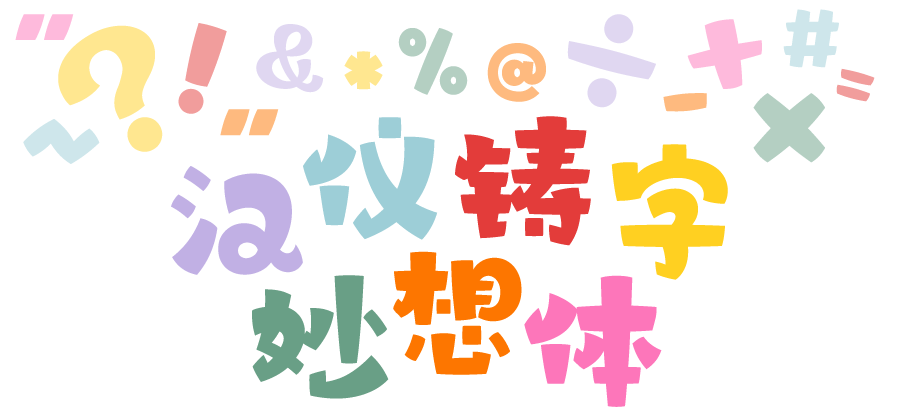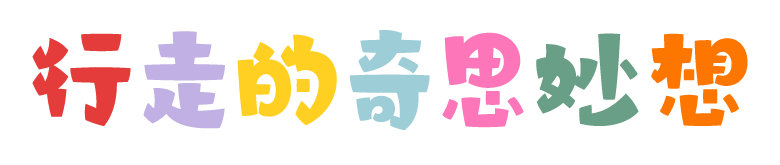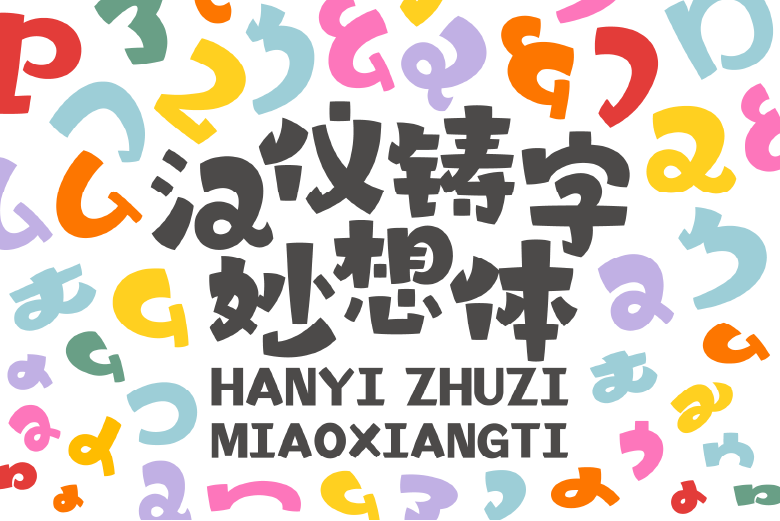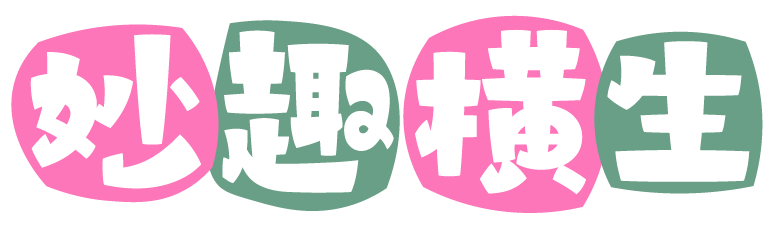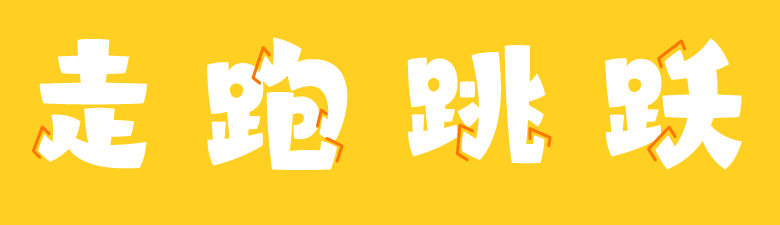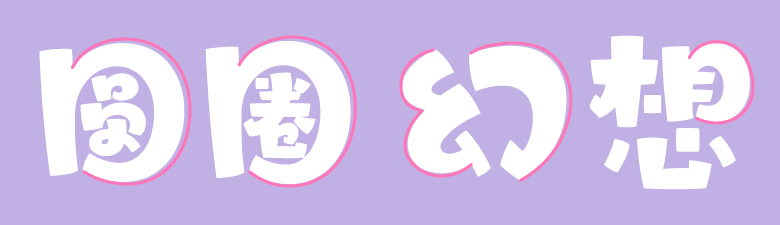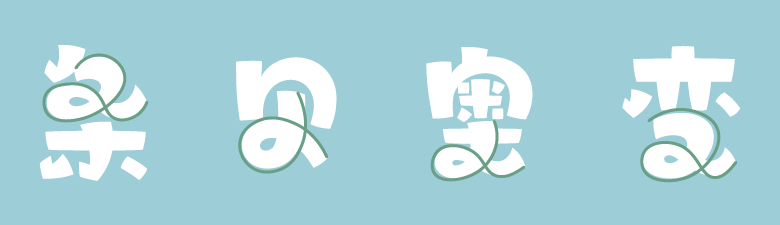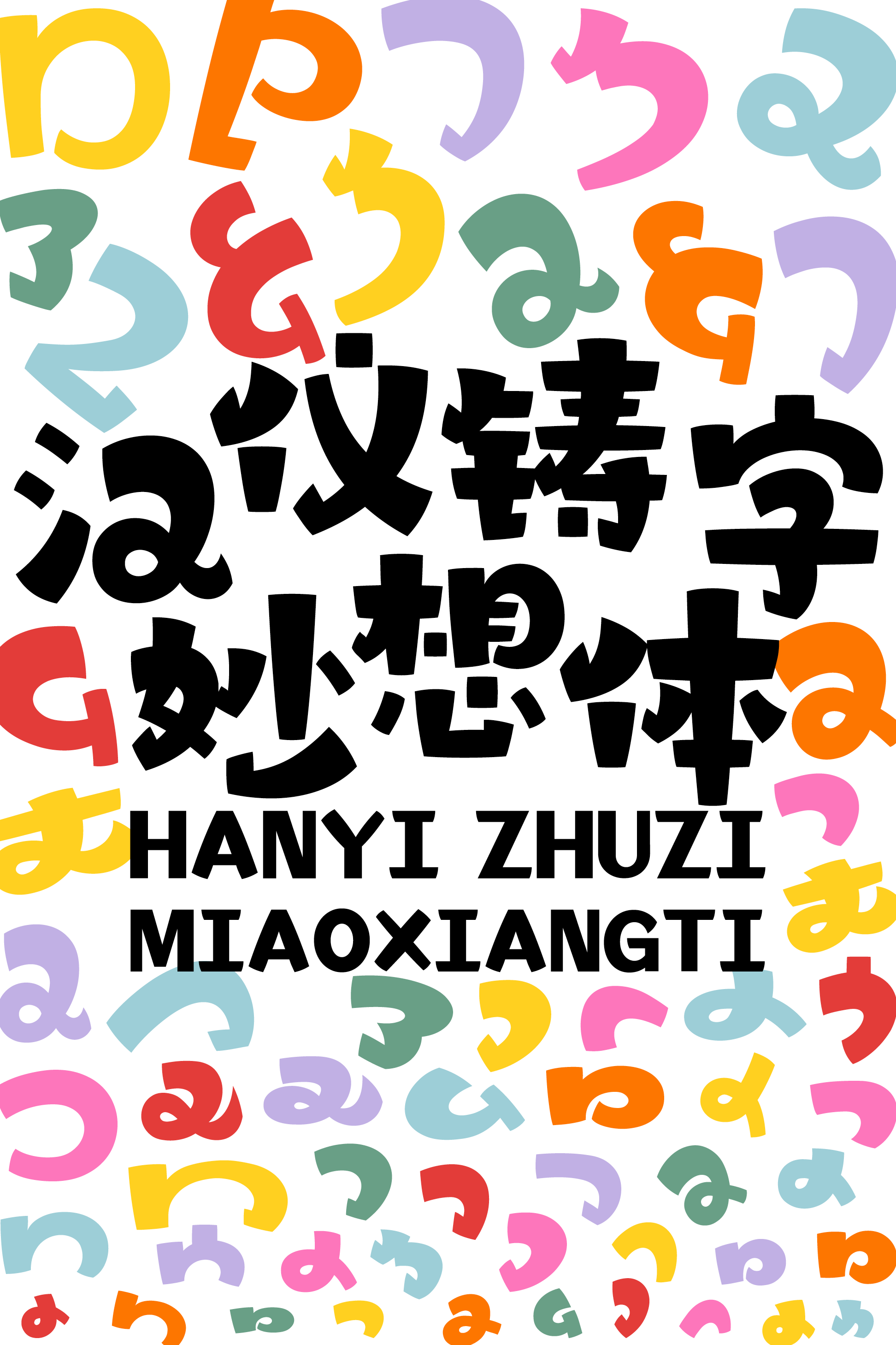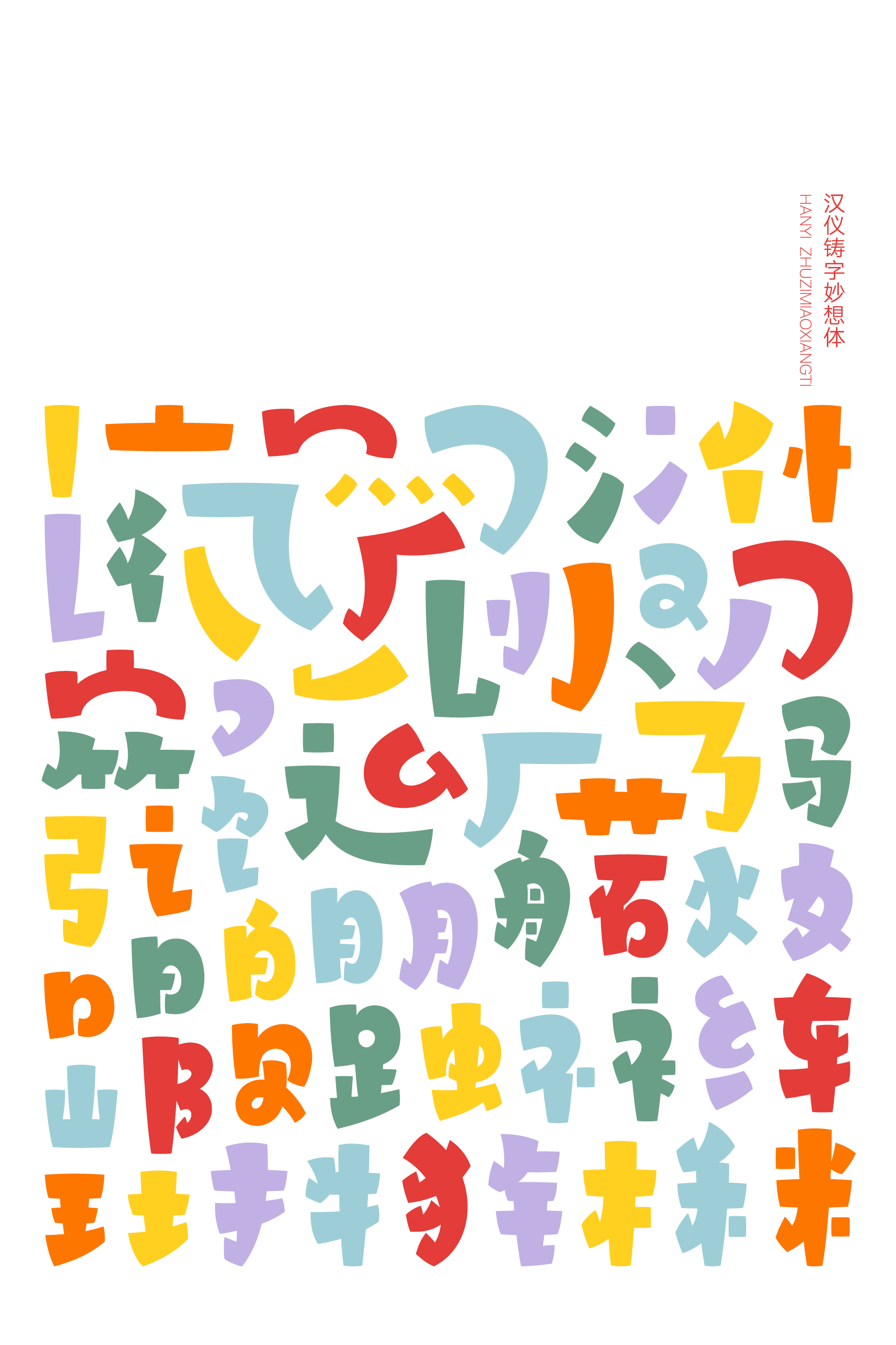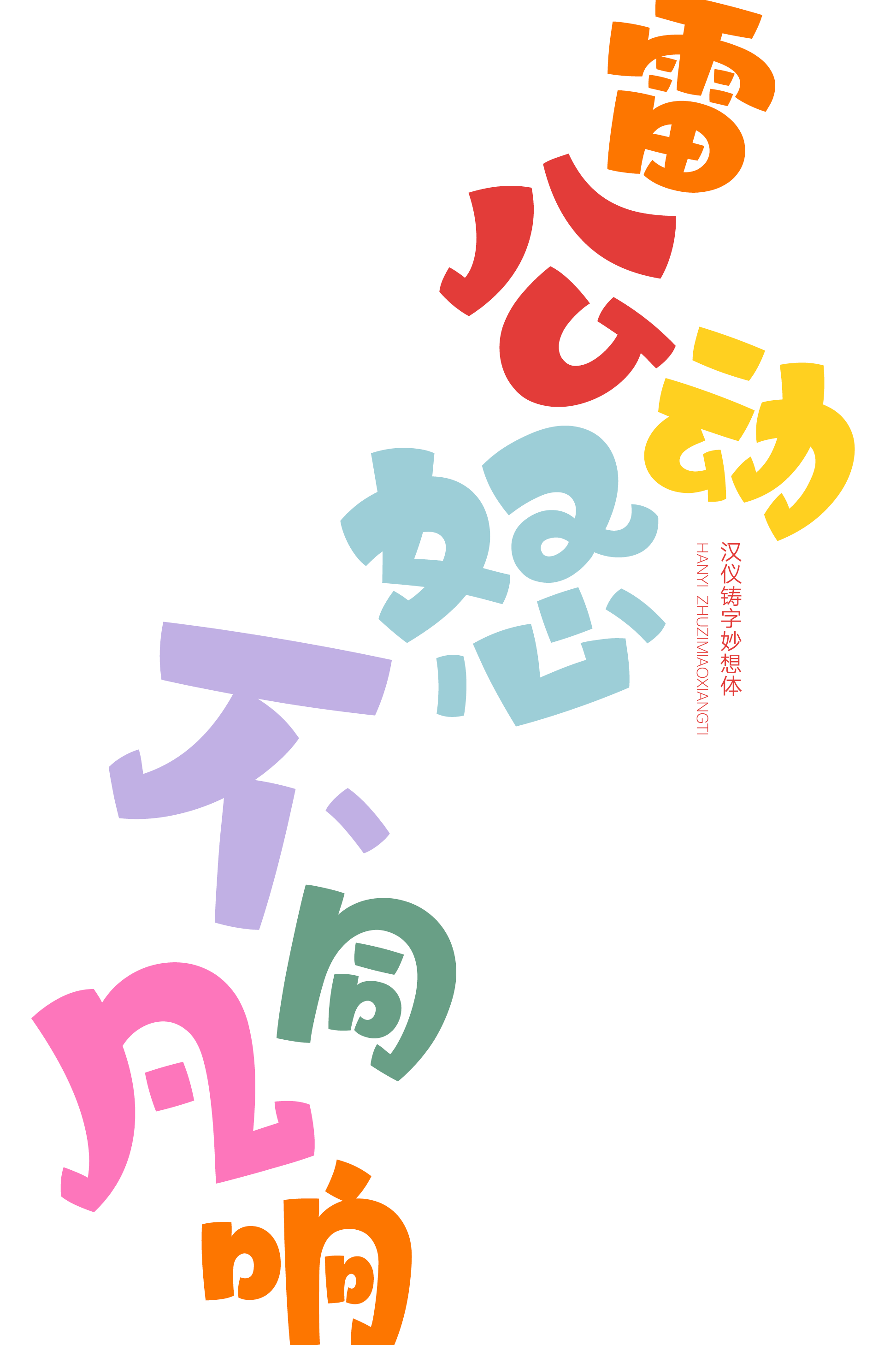
汉仪铸字妙想体字体介绍,让字体奇思妙想起来~
汉仪铸字妙想体是一款活泼可爱的创意设计字体,充满童趣的拟态字形像行走的奇思妙想一般跃动起来。可以广泛作为标题字应用于游戏动漫、影视娱乐、产品包装等领域,尤其适合与儿童相关的主题。
这款字体字面大小各异,视觉效果颇具活力。
字体结构灵活组合,各个部件的穿插自然和谐。
汉仪铸字妙想体的笔画设计处处可见巧思,小小的文字之间有大大的趣味:
收笔处理成小脚丫一样的装饰性方形衬角。
折笔简化处理成饱满的圆弧形。
连笔为灵活的字形增添了连贯性。